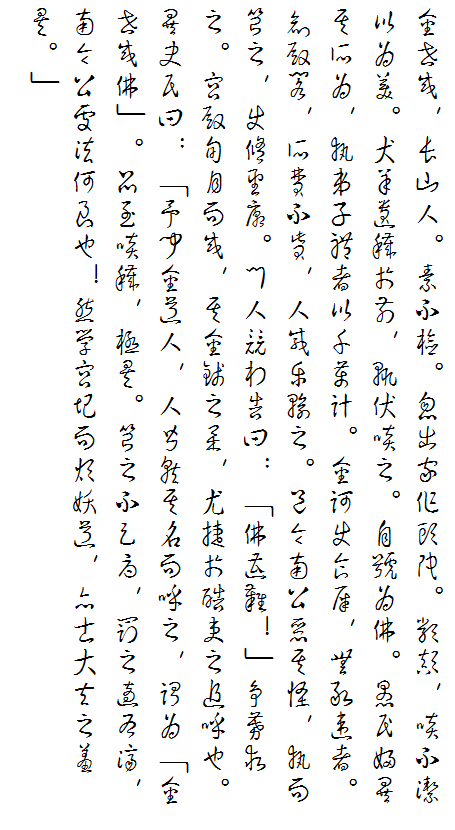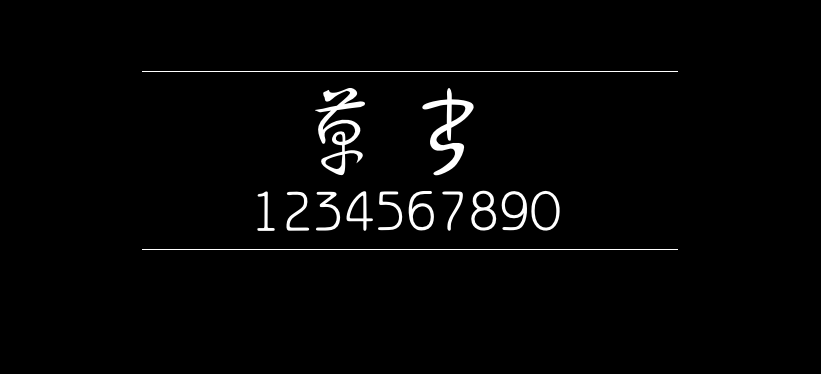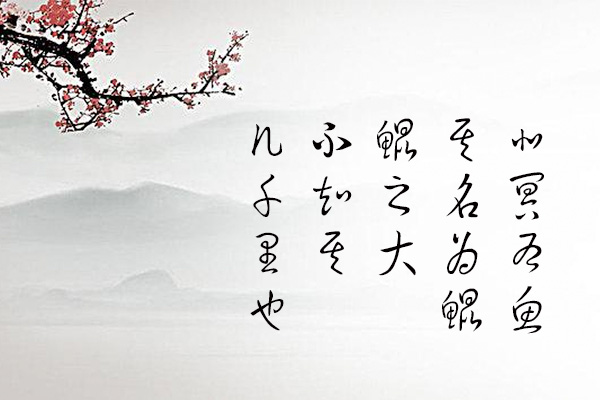
草书
草书字体是百度贴吧一位大神mikhailcai自制的狂草字体。主要模仿孙过庭的字。因为他的字变化不多,容易规范。繁体,一共17000多个字,覆盖四书五经,四大名著和常见字。字体的作者在贴吧上表示这款字体免费使用,作者并放弃版权,大家可以随便使用。原版的字体只支持繁体中文(输入法裡设置繁体),后来网友落霞孤鹜为了方便大家,制作了一个简入繁出的版本,即输入简体字也能正常输出繁体字,大家可以根据需要安装。
不过对于一简对多繁的情况不太好处理,如「钟」分别对应着「鐘」和「鍾」(最后取了「鈡」,与简体形近),「发」分别对应「發」和「髮」(取「發」,因为「发」字是「發」的草书楷化)等;其他在常用字范围内一对一的,取对应的繁体字(正体字),不改成形近字或该简体字所来源的异体字,如「钥」取「鑰」而不取「鈅」,「坝」取「壩」而不取「垻」,「铁」取「鐵」而不取「鉄」等。
下图为聊斋第二卷的《金世成》样例。